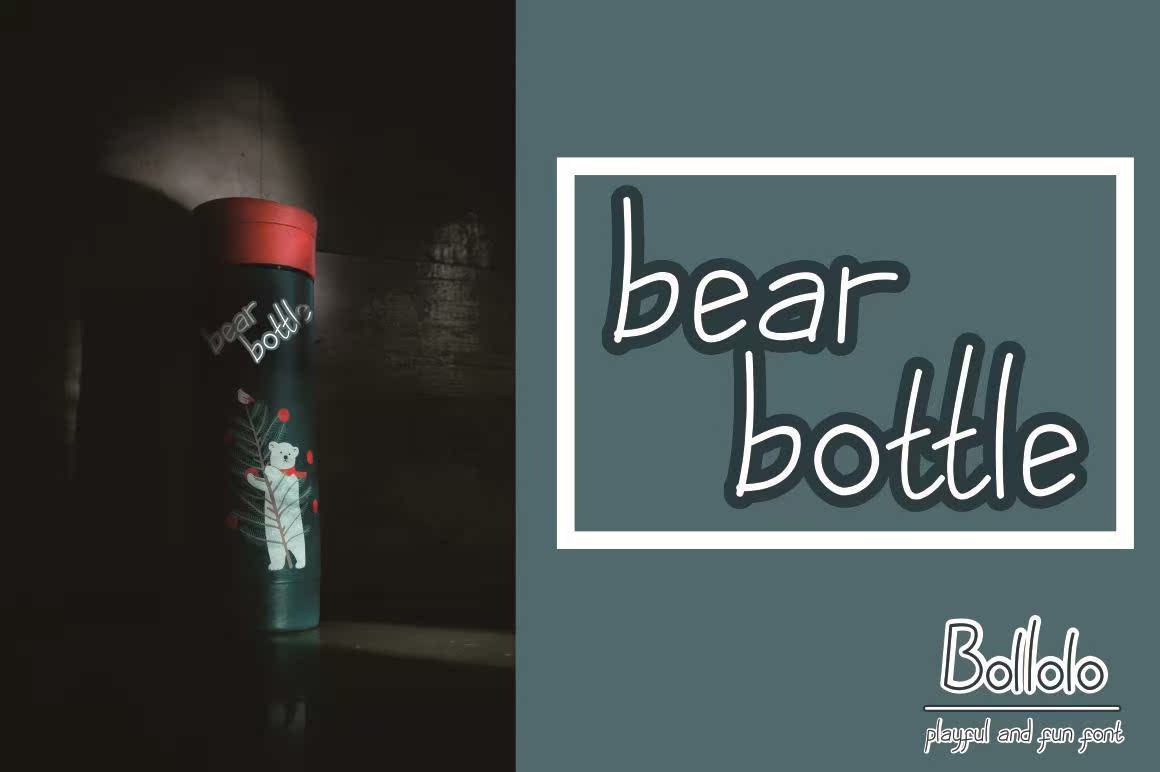
Bollolo(手写)是有趣和好玩的字体。Bollon是Bolo Bolow的缩写,意思是beforiend。这种字体可读、朗朗上口、简单。这种字体适用于引用、标志设计、kidstoys、故事书和许多其他设计项目。Bollolo(手写)是有趣和好玩的字体。Bollon是Bolow的缩写,意思是beforiend。Font是可读、朗朗上口,此字体适用于引用、标志设计、儿童玩具、故事书和其他许多设计项目。